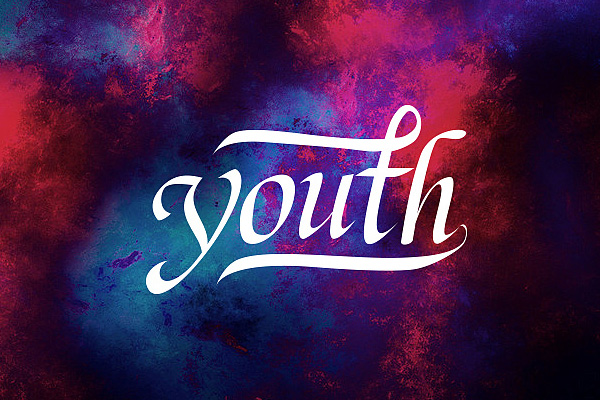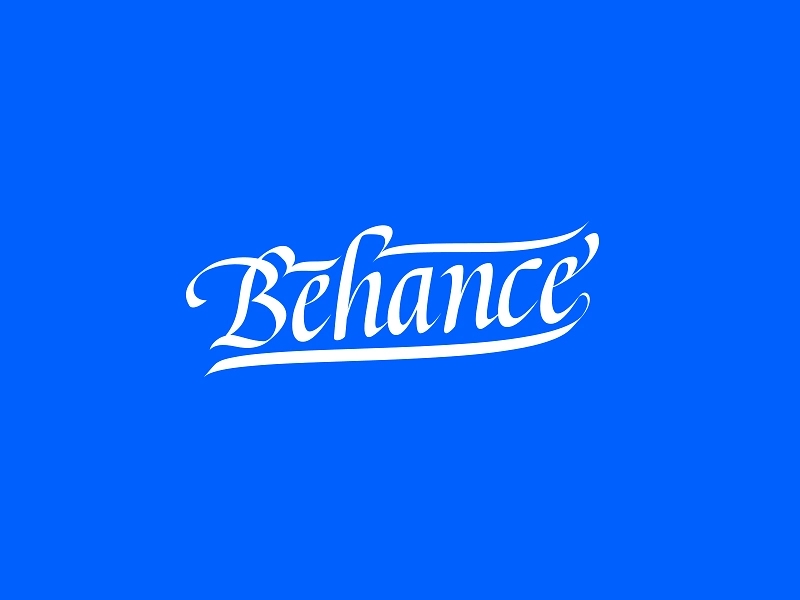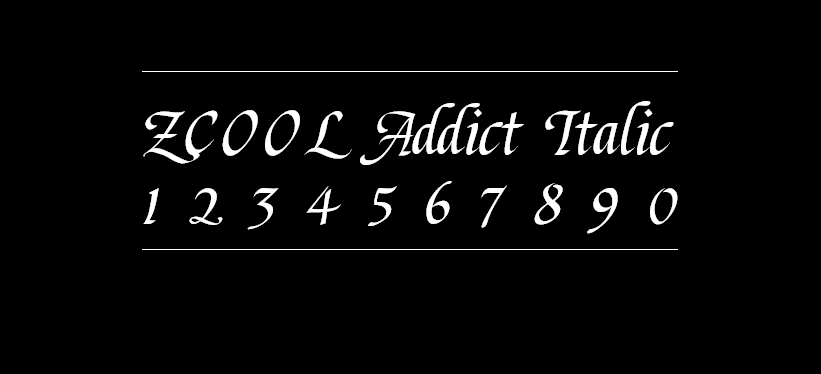
站酷意大利体字体介绍
站酷意大利体是由大猫Addict设计,站酷冠名的首款公益西文字库, 是可免费商用的西文字。站酷意大利体是手写的意大利体风格,通过平行笔手写大量字母,挑选写的还不错的进行扫描,最后矢量处理成英文字库,并生成了TTF字体文件,下载的压缩文件中有三个文件,ZCOOL Addict Italic 01、ZCOOL Addict Italic 02两个字体安装文件和一个包含字母和标点的AI文件。01与02的区别主要是小写字母的写法有所不同,实际使用中两者可结合使用。
站酷意大利体字体应用示例